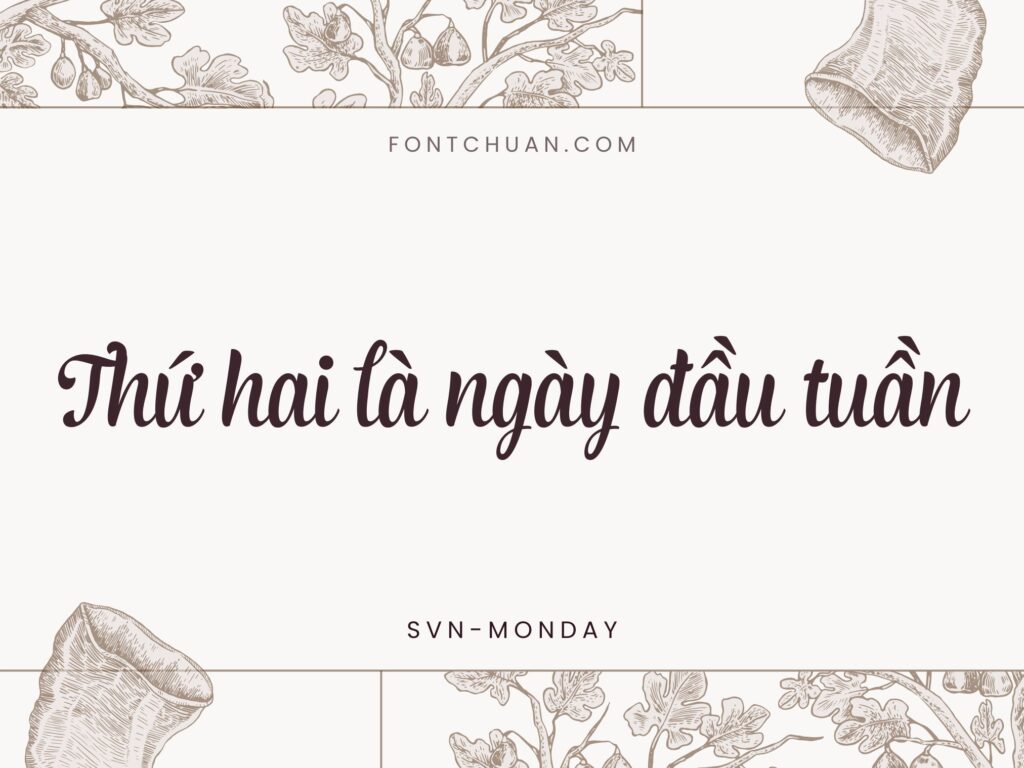
Font SVN Monday Việt Hóa
Tác giả Font: Emil Karl Bertell
Font SVN Monday là phiên bản Việt hóa của kiểu chữ Monday, được thực hiện bởi STYLEno.1 Fonts. Monday là một kiểu chữ script hiện đại với các nét chữ mềm mại và thanh lịch, tạo cảm giác thân thiện và gần gũi. Font này bao gồm đầy đủ các ký tự chữ hoa, chữ thường, chữ số và dấu câu, hỗ trợ đa ngôn ngữ. Monday phù hợp cho nhiều mục đích sử dụng khác nhau như thiết kế thiệp mời, logo, tiêu đề, bao bì sản phẩm và các ấn phẩm truyền thông.
SVN Monday lý tưởng cho các dự án thiết kế yêu cầu sự mềm mại và thân thiện, như thiết kế thiệp mời, logo thương hiệu và các ấn phẩm truyền thông. Các ngành nghề như thiệp cưới, giáo dục và ẩm thực có thể tận dụng font này để tạo điểm nhấn trong thiết kế. Ngoài ra, font cũng thích hợp cho các sự kiện như Valentine, Sinh nhật, Tết và các lễ hội khác.